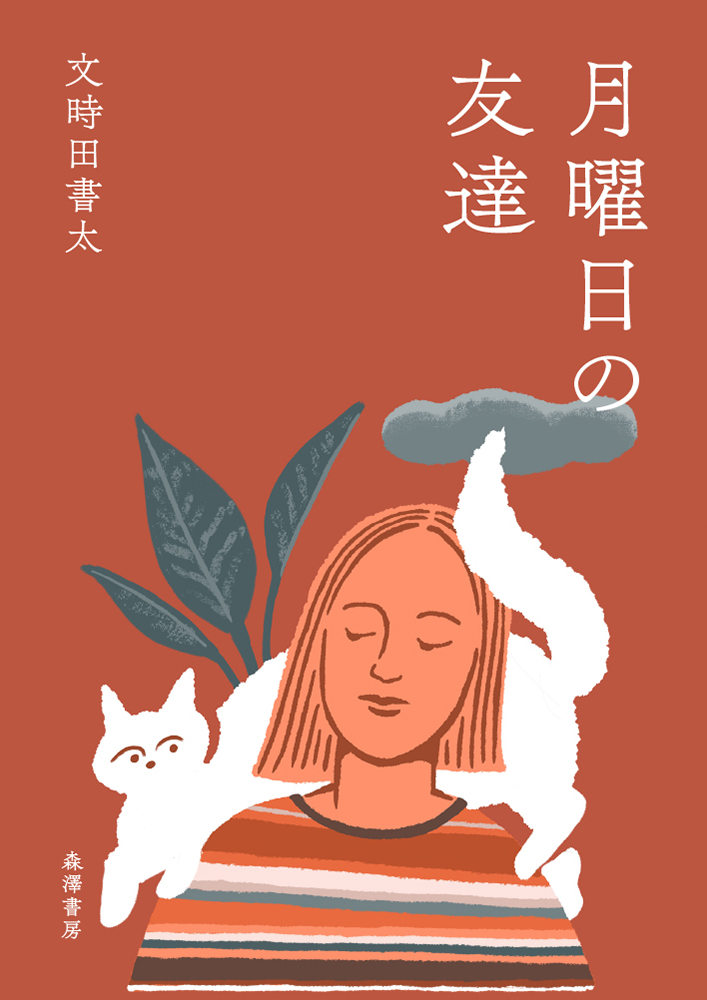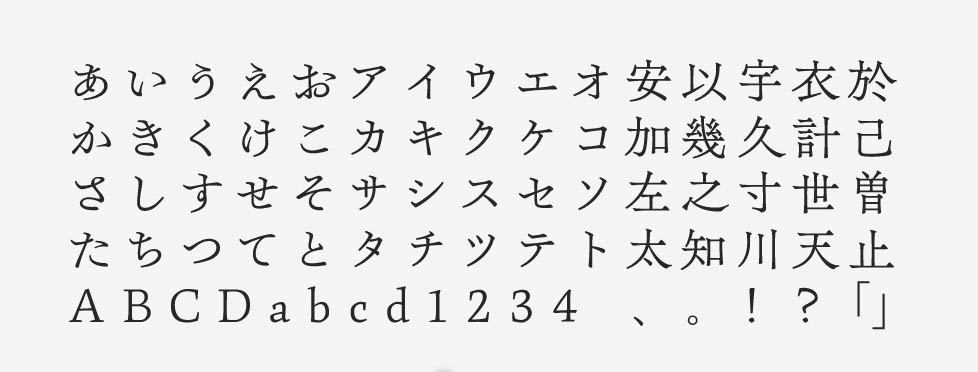
「霞青藍」について
2022年に登場したオールドスタイルの明朝体です。文字の固有の形を重視してデザインされています。漢字には楷書に由来する特徴が色濃く残されており、そこへ1940年代から1960年代頃の活字にヒントを得た平仮名を組み合わせています。欧文の骨格のベースは15世紀末の活字です。
「霞青藍」の特徴
霞青藍の文字は全体的にふところが絞られていて、横線やハライでは伸びやかさが強調されています。明朝体と楷書体のエッセンスがバランス良く混ざったフォントです。
同時リリースの霞白藤と共通の骨格・字形の漢字を備えていますが、細部の筆致には違いがあり、霞青藍はより無骨さや風格を感じさせる印象です。特に書籍のタイトルや文芸雑誌の見出しなどには最適で、クラシカルな雰囲気を演出できます。
作例のような文芸作品のタイトルに最適で、誠実さや真面目さを表現したい場合にも、とても似合うフォントではないかと思います。Z世代以降などは、このクラシカルな感じが新しく感じるのではないでしょうか。これから推していきたいフォントです!